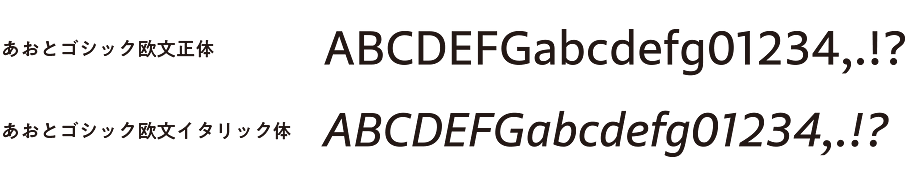
【あおとゴシックについて】
あおとゴシックの特徴
あおとゴシックはAdobe-Japan1-3に準拠しています。
加えて、デフォルトのプロポーショナル欧文に対応するイタリック体を搭載しています。
通常のAdobe-Japan1-3の書体では搭載しないイタリック体を搭載することで、
和欧混植の際の利便性を向上させた書体となっています。
【イタリック体字形一覧】